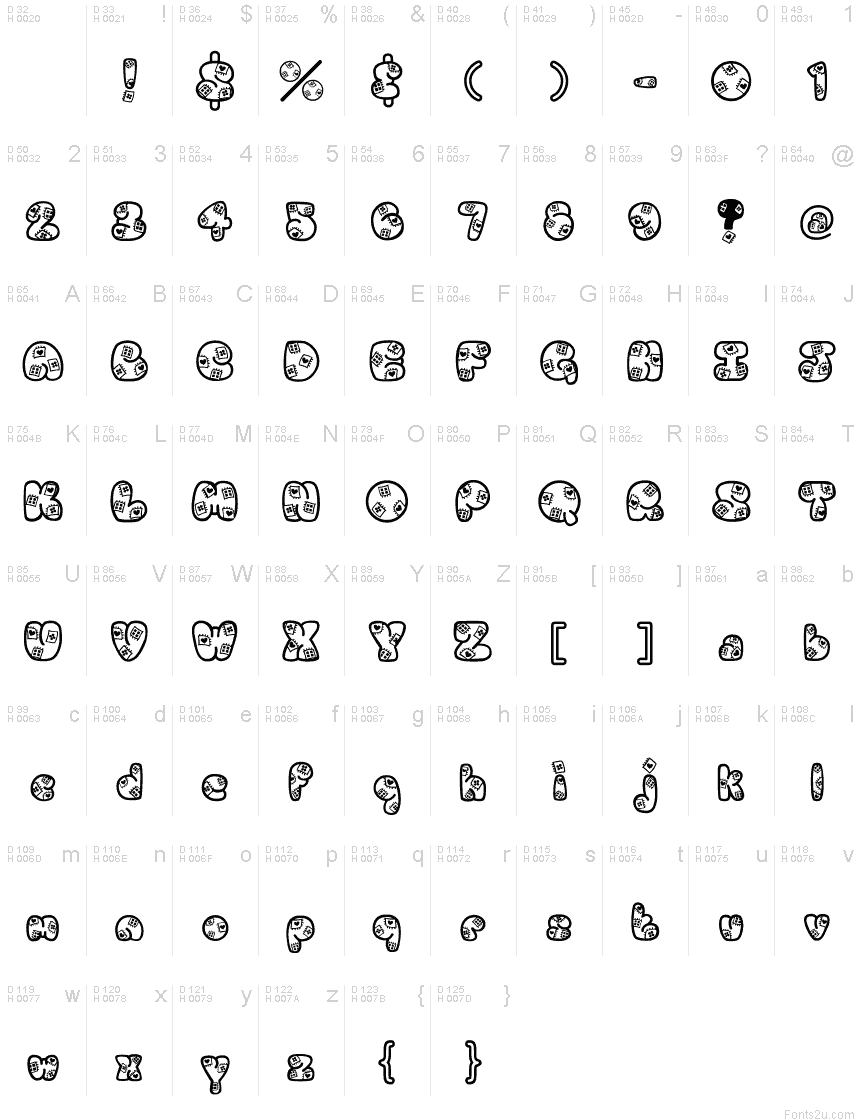
Patches ist eine kostenlose, verspielte Cartoon-Schrift, deren abgerundete Buchstaben aussehen, als wären sie aus weichen Stoffstücken zusammengenäht. Mit ihren sichtbaren Nähten, kleinen quadratischen Flicken sowie Herz- und Blumen-Applikationen wirkt die Schrift wie eine handgefertigte Patchwork-Decke und nicht wie ein einfaches Novelty-Design.
Damit ist sie die ideale Wahl für Einladungen zu Kindergeburtstagen, Flyer für Bastelmessen, Überschriften in Scrapbooks, Blog-Header zum Thema Nähen oder verspielte Produktetiketten. Die liebevollen Details verleihen kurzen Wörtern einen einzigartigen Charakter – perfekt für handgemachtes Branding oder saisonale Dekorationen, bei denen eine zu glatte Display-Schrift einfach deplatziert wirken würde.
Patches